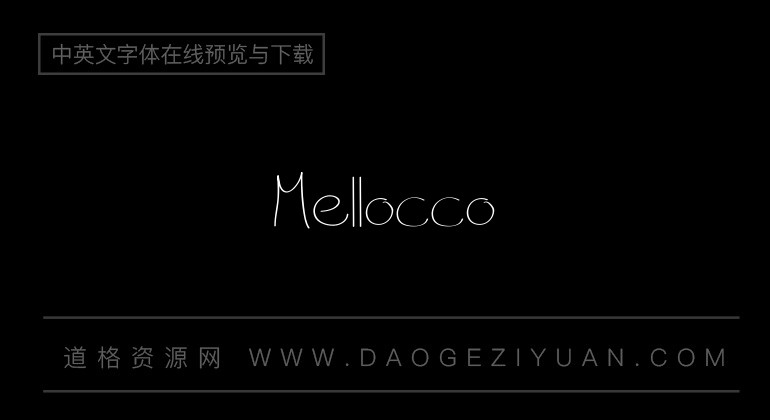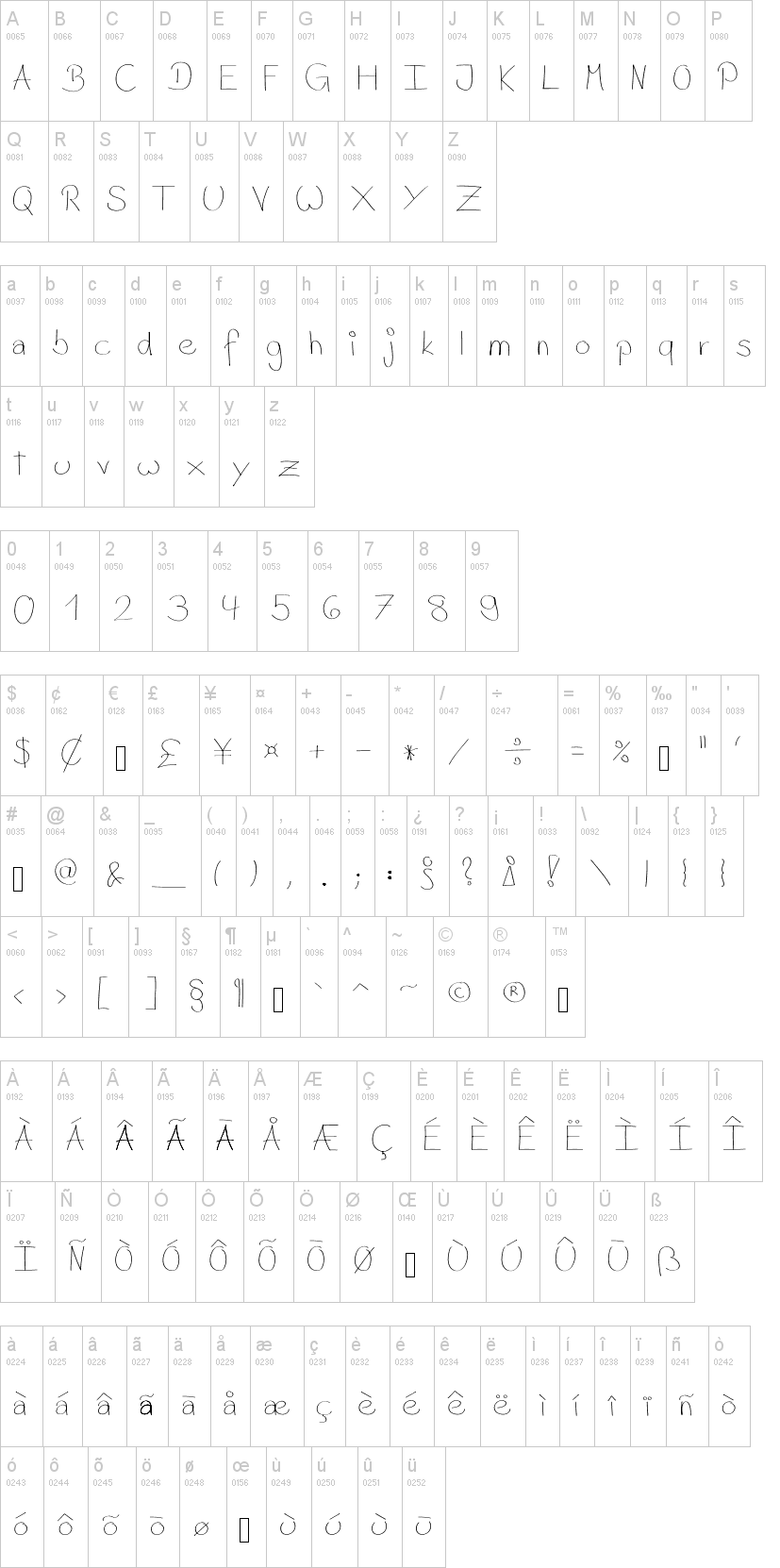
Mellocco是一款基于美式手写体设计的字体,由西班牙设计师Gustavo Dipre创作。它拥有一种柔和的、温暖的、简约的风格,充满活力,同时又不失优雅。Mellocco字体可以用于多种场合,比如活动海报、书籍封面、网站标题等,能够很好地展示文字的美感,令人印象深刻。内容介绍
Mellocco是一款非常不错的手写艺术字体,具有很好的视觉感,适合于文化类的宣传设计、商业类品牌的广告和产品包装设计以及个性化文字排版等较多场景。